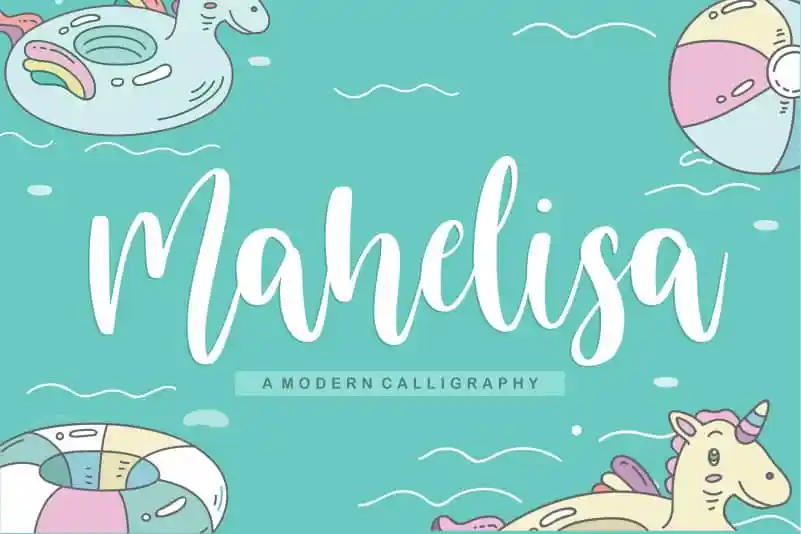
Mahelisa Modern Calligraphy Font – Download Grátis
A Mahelisa Modern Calligraphy Font é perfeita para projetos variados que exigem uma elegância e delicadeza únicas. Com seu design moderno e detalhado, essa fonte consegue traduzir textos até os mais sutis nuances de forma clara e vívida. Ideal tanto para a embalagem dos produtos quanto para o branding, ela traz um toque sofisticado ao seu projeto, tornando-o imediatamente chamativo. Também é uma escolha perfeita para as páginas de revistas ou redes sociais, onde uma frase bem escrita pode destacar suas mensagens com estilo. Além disso, a Mahelisa Modern Calligraphy Font se adequa ao design criativo que busca expressar palavras acima do background, seja em uma festa de casamento ou até mesmo em um projeto pessoal. Ela permite que você transforme qualquer ambiente em algo único e memorável, deixando seu trabalho mais especial. Com o uso da Mahelisa Modern Calligraphy Font, é possível alcançar um equilíbrio perfeito entre a simplicidade dos estilos modernos e o charme clássico do calligrafismo. É uma fonte versátil que se encaixa em diversos ambientes de design, tornando seu trabalho ainda mais personalizado e imprimível.